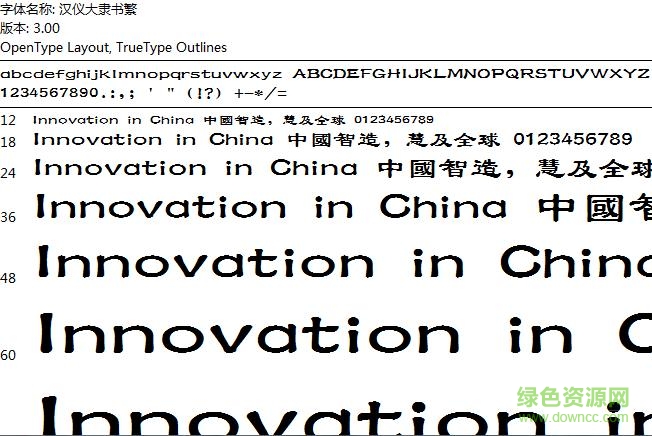
hyf1gf
hyf1gf字體是一款經(jīng)過(guò)藝術(shù)加工之后的隸書(shū)字體,在繼承了隸書(shū)優(yōu)秀特質(zhì)的基礎(chǔ)上進(jìn)行了符合現(xiàn)代審美的加工,讓隸書(shū)在電腦上煥發(fā)全新的光彩,喜歡趕緊下載使用!
hyf1gf字體簡(jiǎn)介
hyf1gf字體就是我們常說(shuō)的漢儀大隸書(shū)繁體字體,是漢儀字庫(kù)打造的一款古代書(shū)法字體,根據(jù)經(jīng)典的隸書(shū)字體演變而來(lái),融入現(xiàn)代設(shè)計(jì)氣息,顯得非常的美觀!